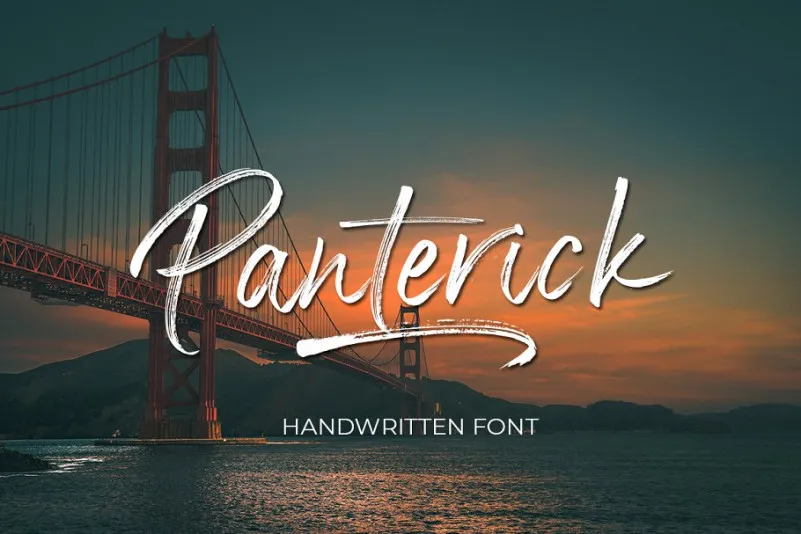
Panterick Brush Font – Download Grátis
Através do designer 1001fonts, chegamos à introdução de uma nova opção no mundo das fuentes script, a Panterick Brush Font. Esta elegante e única tipografia foi criada com um estilo de letra manuscrita cuidadosa, projetada para oferecer flexibilidade em diversas aplicações designísticas. A sua utilização perfeita abrange desde logomarcas até às impressões de t-shirts, os headlines nos jornais e websites, as fórmulas nas revistas ou o desenvolvimento dos cartões comerciais. Companheiro de design, a Panterick Brush Font oferece uma solução versátil para aqueles que procuram um elemento único em suas criações. Este estilo elegante irá enriquecer seus trabalhos e dar-lhe o diferencial que tanto busca. E não se limite ao design; este é também um recurso perfeito para a elaboração de posters, cartões de visita ou qualquer outro tipo de projeto que deseje apresentar com um toque especial. Sinta-se à vontade para explorar a vasta gama de possibilidades criativas oferecida pela Panterick Brush Font.